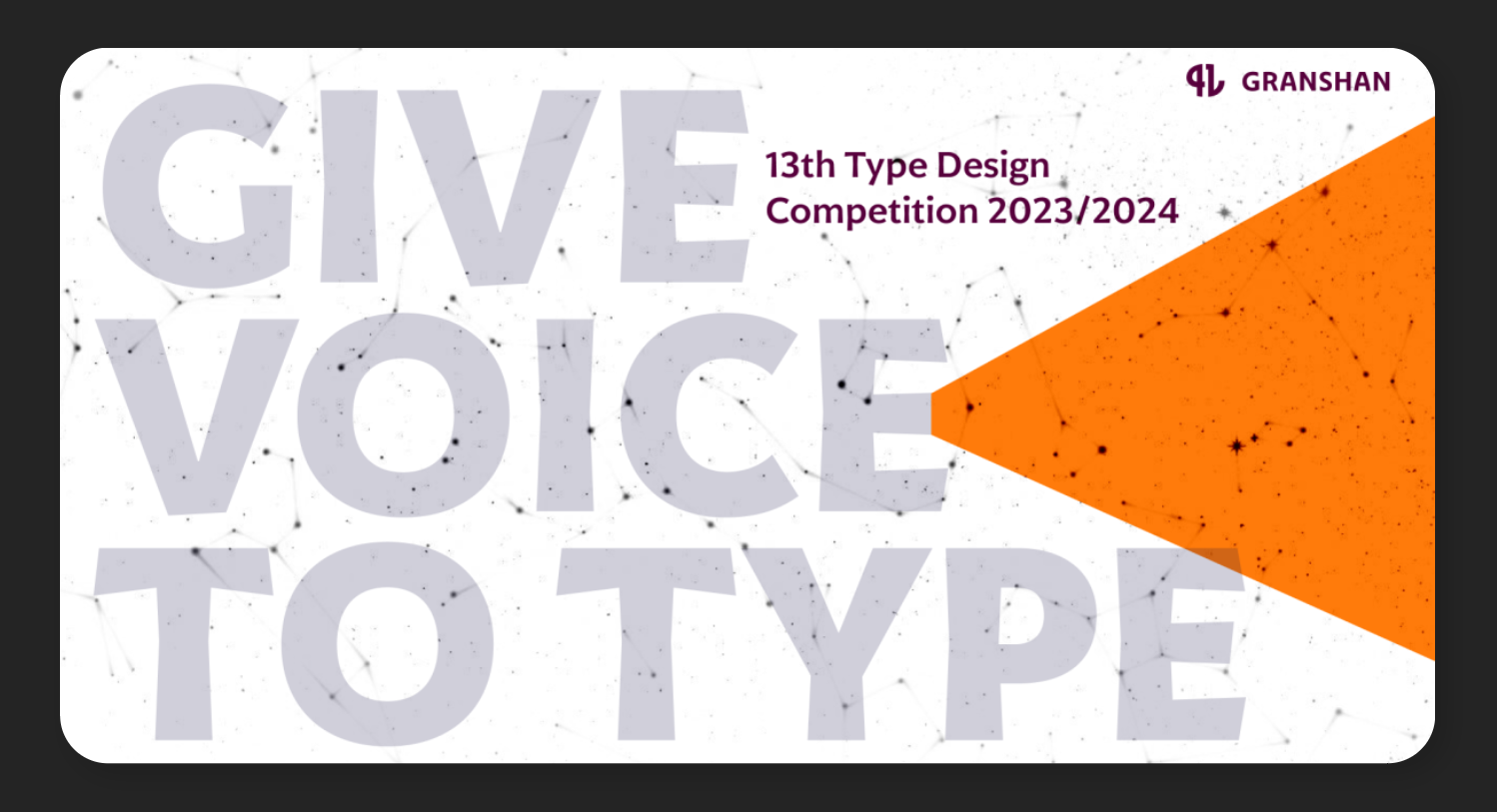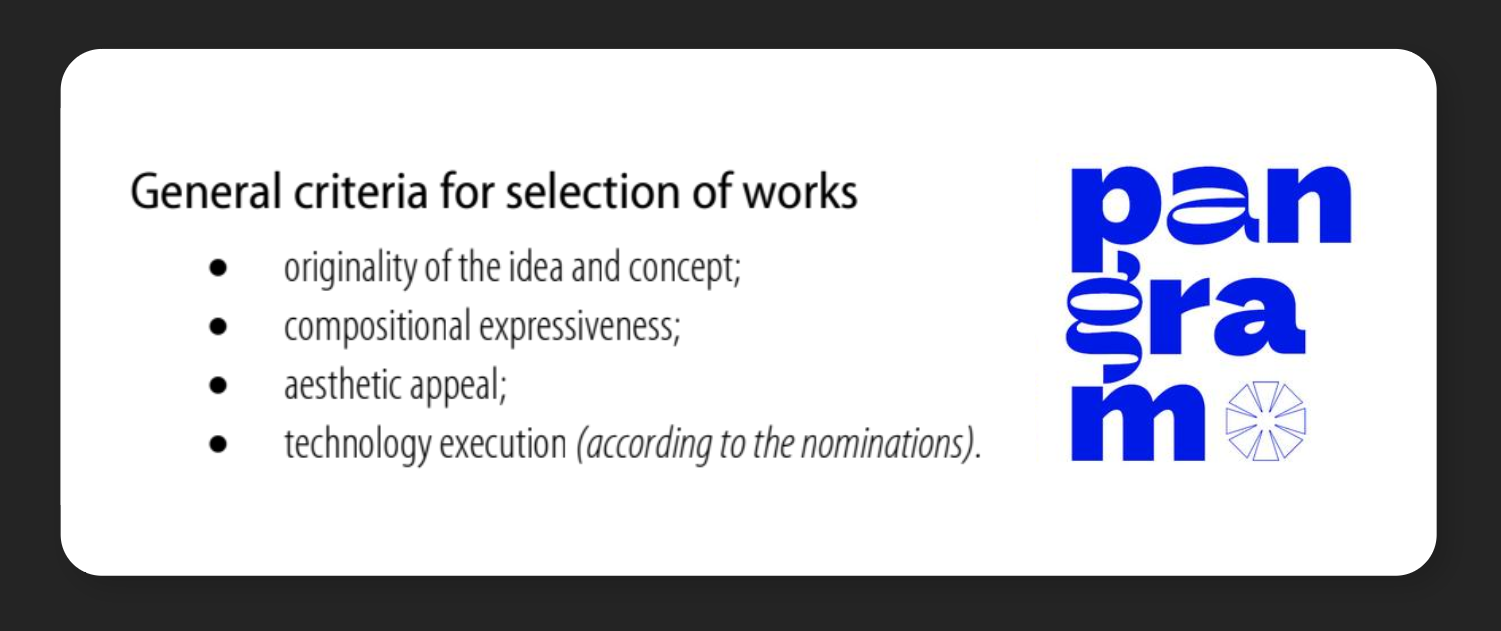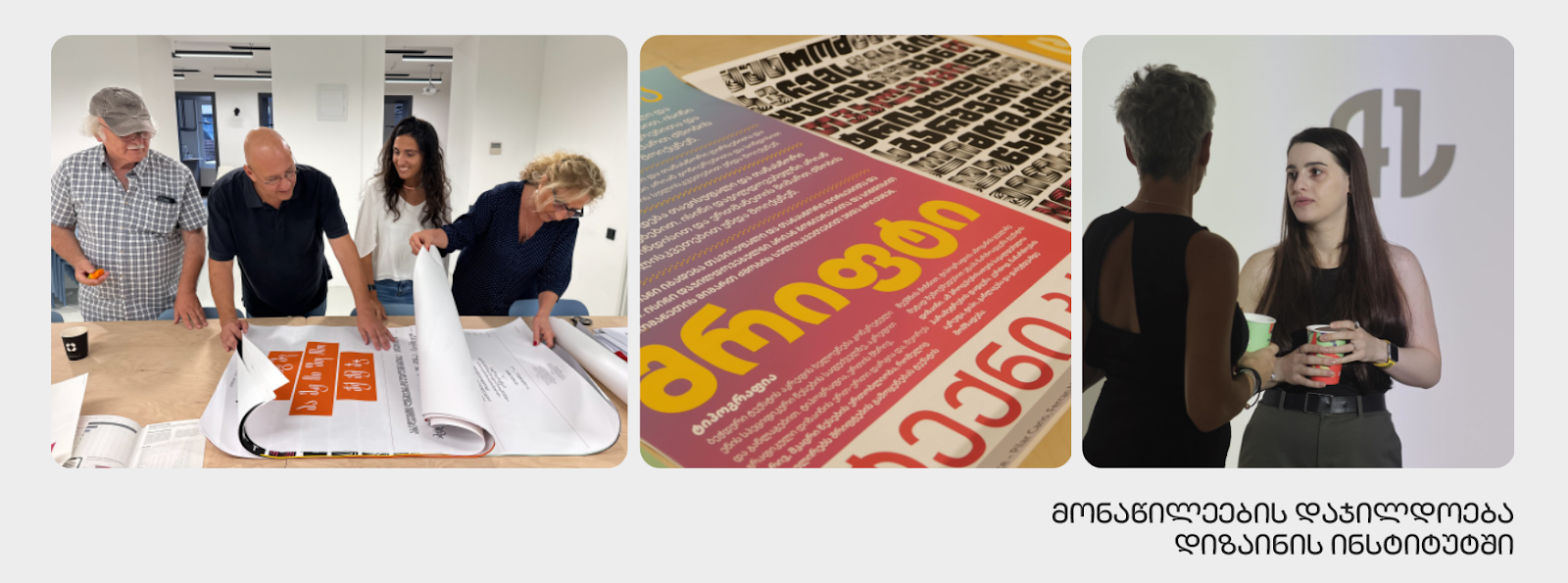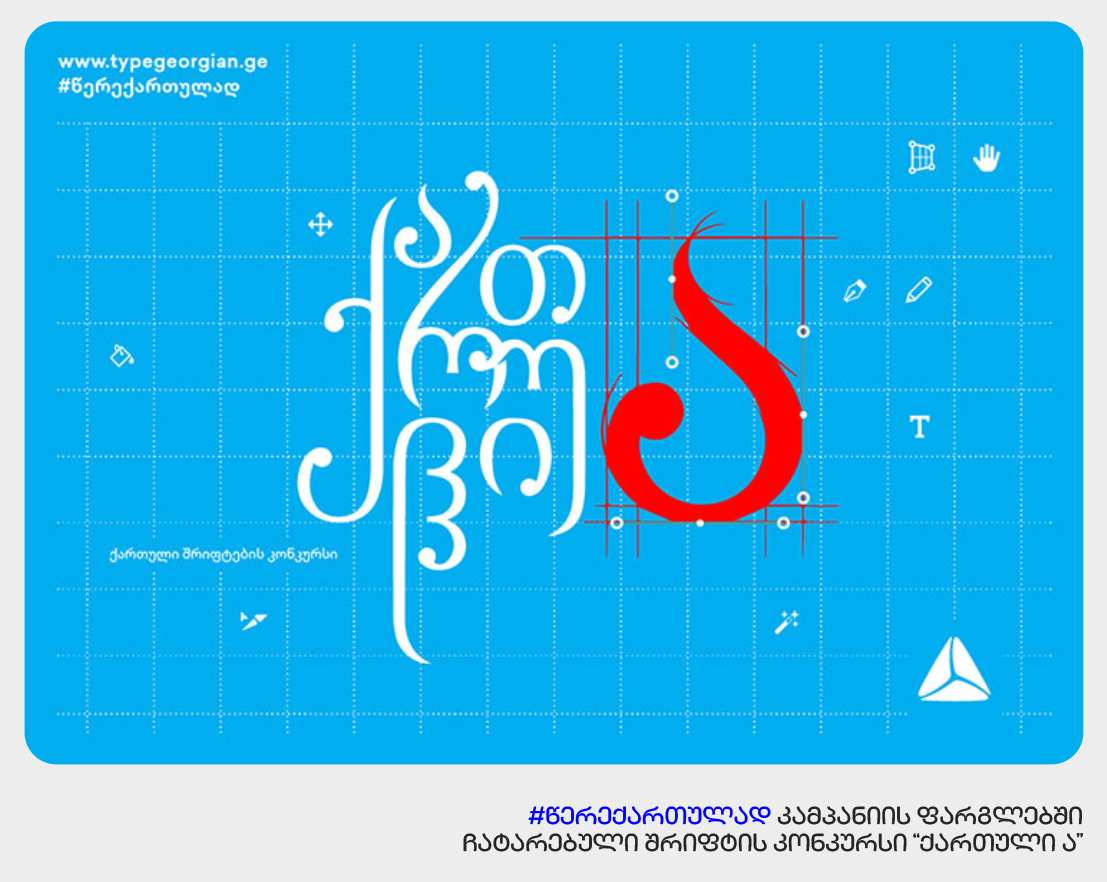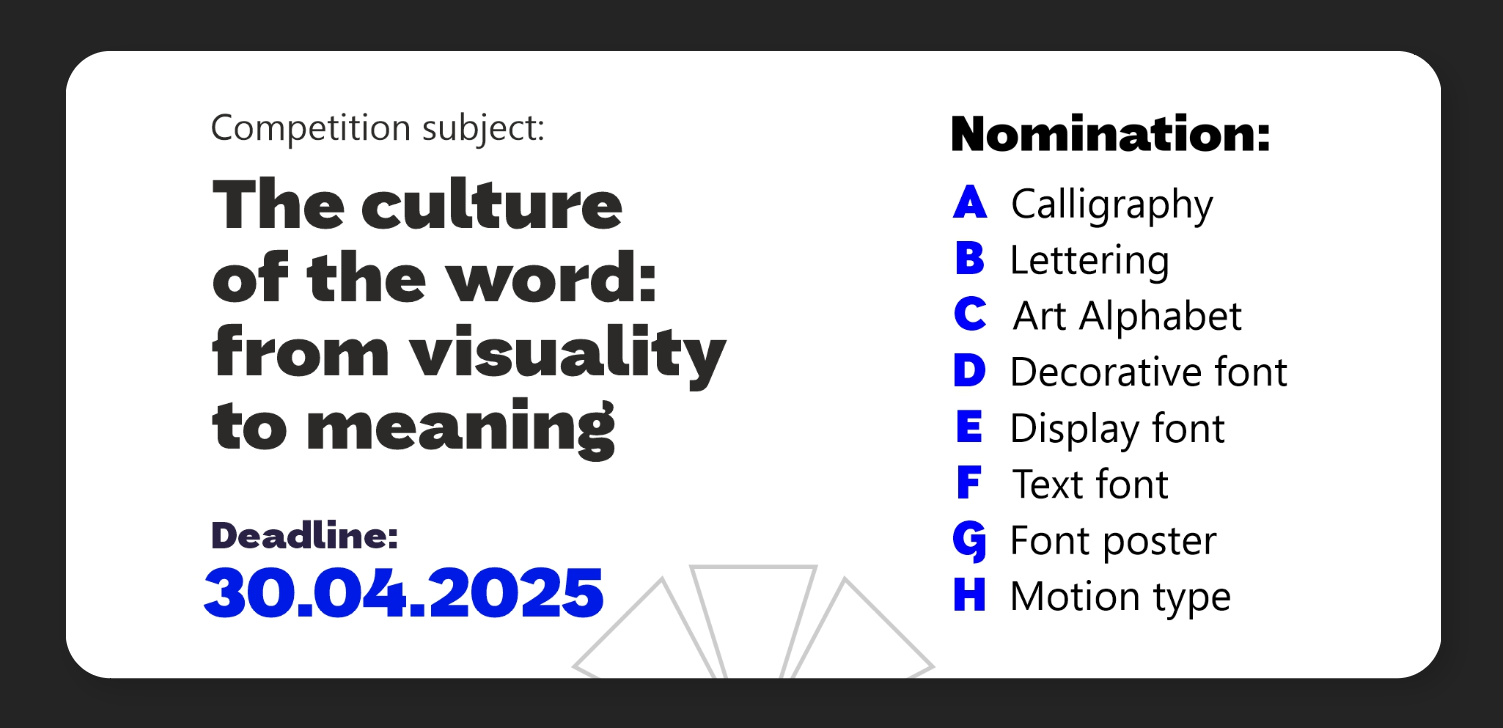
ფონტის დიზაინერი მერაბი გეწაძე უკვე მესამე წელია, რაც უკრაინული საერთაშორისო კონკურსის Pangram - International Student Competition on Font and Calligraphy-ის ჟიურის წევრია. ეს ფაქტი კიდევ ერთხელ უსვამს ხაზს მის პროფესიონალიზმს და იმ ნდობას, რომელსაც საერთაშორისო ტიპოგრაფიული სივრცე ავლენს ქართული დიზაინის მიმართ.
ბოლო წლებში ქართული ფონტების ხილვადობა გლობალურ არენაზე მნიშვნელოვნად გაიზარდა. ამის მაგალითია Granshan-ის მე-13 საერთაშორისო არალათინური შრიფტის კონკურსი, სადაც ქართული ანბანი ოფიციალურად დაემატა კონკურსში მონაწილე დამწერლობათა სიას, როგორც მეათე და მერაბი ასევე ჟიურის წევრებს შორის იმყოფებოდა. აღსანიშნავია, რომ სწორედ იმ წელს ქართველმა დიზაინერმა, ანა სანიკიძემ, პირველი ადგილი და კონკურსის მთავარი პრიზი მოიპოვა, ხოლო სხვა ქართველმა მონაწილეებმაც (ნიკა ხიპაშვილი, ლაშა გიორგაძე,ალექსანდრე სუკიასოვი, სერგო ტიტენკოვი) არაერთი პრიზი მიიღეს სხვადასხვა კატეგორიებში.
ალბათ ყველა დიზაინერისთვის საინტერესოა, როგორ მიიღოს მონაწილეობა კონკურსში, როგორ აფასებს საერთაშორისო კონკურსში მონაწილეებს ჟიური და რა გავლენას ახდენს კონკურსებში ქართველების ხილვადობა ქართული შრიფტის დიზაინის მომავალზე. ამაზე სასაუბროდ მერაბ გეწაძეს დავუკავშირდით:
გილოცავთ Pangram-ის შრიფტების კონკურსის ჟიურის წევრად კიდევ ერთხელ შერჩევას! როგორც ვიცით, უკვე მესამე წელია, რაც ჟიურის წევრებს შორის ხართ საქართველოს სახელით. როგორ ჩაერთეთ პირველად კონკურსში?
მადლობა, რომ დაინტერესდით ამ თემით, მსგავსი პუბლიკაციები ხელს უწყობს ქართული დამწერლობისა და შრიფტის მნიშვნელობის პოპულარიზაციას თანამედროვე საზოგადოებაში.
“PANGRAM”-ის კონკურსის ჟიურიში ჩართვა შემომთავაზა „გრანშანის“ ერთერთმა დამფუძნებელმა ედიკ ღაბუზიანმა. ჟიურიში ჩვენი წარმომადგენლის დამატება თავისთავად აჩენს კონკურსში ქართველი მონაწილეების აქტიურობის მოლოდინს.
რას ნიშნავს თქვენთვის საქართველოს წარმოჩენა ასეთ ცნობილ საერთაშორისო კონკურსში?
ქართველ მონაწილეთა ნებისმიერი საერთაშორისო აქტივობა მნიშვნელოვანია ზოგადად საქართველოს და ამ შემთხვევაში ქართული დამწერლობის პოპულარიზაციისათვის. თუ გავითვალისწინებთ ჟიურის და იმას, რომ მონაწილეთა მრავალეროვნული შემადგენლობის თვალთახედვაში ქართული დამწერლობის ნიმუშები მოხვდა, „Pangram“-ი სასარგებლო და მნიშვნელოვანი სივრცეა, როგორც ქართული დამწერლობის გაცნობისათვის, ასევე სტუდენტთა სტიმულირებისა და სამომავლოდ პროფესიონალებად ჩამოსაყალიბებისთვის.
თქვენი აზრით, რით არის Pangram-ის შრიფტების კონკურსი უნიკალური - რით განსხვავდება ის სხვა შრიფტების დიზაინის კონკურსებისგან?
ყველა კონკურსი თავისთავად უნიკალურია. „Pangram“-ის ყოველ ახალ კონკურსს გააჩნია თავისი თემა-დევიზი, რაზეც მორგებულია მთლიანად საკონკურსო ნამუშევრების ხასიათი.
გარდა ამისა, წარმოდგენილი ნიმუშები თავისი ვიზუალური თუ შემოქმედებითი ჩანაფიქრით ფართო დიაპაზონისაა და ზოგჯერ ცდება კიდეც შრიფტის სახასიათო ტრადიციულ ზღვარს, რაც არაა მოულოდნელობა ავტორთა ახალგაზრდული თამამი აზროვნების გათვალისწინებით.
რამდენად დაინტერესებულები არიან და აქტიურად ერთვებიან თუ არა ქართველი დიზაინერები Pangram-ის კონკურსში?
ქართველი ავტორების აქტიურობა კონკურსში სასურველზე მცირეა. მიუხედავად იმისა, რომ რამდენადაც შეგვიძლია მოვუწოდებთ მონაწილეობისაკენ, ვფიქრობ, საჭიროა დრო, რომ პოპულარული გახდეს კონკურსი.
როგორც ჟიურის წევრი, რა არის ყველაზე მნიშვნელოვანი თვისებები, რომლებსაც ეძებთ შრიფტში?
ერთი გამორჩეული თვისება, რაც განაპირობებს შრიფტის შეფასების ხარისხს - არ მაქვს. კონკურსი რამდენიმე კატეგორიას მოიცავს და შესაბამისად შეფასების მიდგომებიც სხვადასხვაა. ძირითადი კრიტერიუმებია: ორიგინალობა, კომპოზიციური მიმზიდველობა, ესთეტიური გამომსახველობა და შესრულების ტექნური მხარე.
როგორ აბალანსებთ ტექნიკური სიზუსტის შეფარდებას კრეატიულობასთან და ორიგინალურობასთან ნამუშევრების შეფასებისას?
რადგან ჟიურის წევრებს მხოლოდ რასტრული გამოსახულებები გვეგზავნება და არა ვექტორული, ტექნიკური სიზუსტის შეფასება ხილულ ზღვარს არ ცდება. სამაგიეროდ, ასეთი გამოსახულება საკმარისია ნამუშევრის სხვა კრიტერიუმებით შესაფასებლად. ჩემი შეხედულებით, წარმოდგენილ ნიმუშებში ტექნიკური სრულყოფა ავტორთა მიერ არცაა პირველხარისხოვანი და პრიორიტეტი უფრო ორიგინალობაზე და შემოქმედებით მიგნებებზე კეთდება.
მოდით, ვისაუბროთ GRANSHAN-ის კონკურსზე. თქვენ იქაც საქართველოს წარმომადგენელი ჟიურის წევრებს შორის იყავით, რაც დიდი მიღწევაა. რით განსხვავდებოდა ეს გამოცდილება Pangram-ისგან?
GRANSHAN-ი თავიდანვე პროფესიონალების ჩართულობაზეა ორიენტირებული და შესაბამისად დონეც უფრო მაღალია. ნამუშევრების ვიზუალზე მოთხოვნა ბევრად უფრო დეტალურია და რამდენიმე შაბლონშია წარმოდგენილი, რაც განაპირობებს მაქსიმალურად კრიტიკულად იქნეს შეფასებული ხარისხი. თავდაპირველად, დამწერლობის ჟიურის ყველა წევრის მიერ ხდება ნამუშევრების განხილვა და შეფასება. შემდეგ ეტაპზე შეფასებაში მონაწილეობენ მხოლოდ ათივე დამწერლობის ჟიურის თავმჯდომარეები და კონკურსის ორგანიზატორებთან ერთად ხდება საბოლოო გამარჯვებულების გამოვლენა.
გარდა კონკურსისა GRANSHAN-ი ატარებს კონფერენციებს მსოფლიოს სხვადასხვა ქალაქებში, სადაც მომხსენებლებად არიან შრიფტის დიზაინის სფეროს როგორც აღიარებული, ასევე ნებისმიერი სპეციალისტები.
GRANSHAN-ის მე-13 შრიფტის კონკურსში (2023/2024) ქართული ოფიციალურად შეიყვანეს წარმოდგენილ დამწერლობებს შორის. რამდენად მნიშვნელოვანი იყო ეს ნაბიჯი ჩვენი ტიპოგრაფიული კულტურისთვის?
კონკურსში ქართული დამწერლობის მეათე ნომინაციად შეყვანა ერთბაშად არ მოხდარა. მას წინ უძღოდა რამდენიმეწლიანი მიმოწერა და ონლაინ ჩართვები ასოციაცია „ქართული შრიფტისა“ და GRANSHAN-ის ორგანიზატორებს შორის. ამ პროცესის ინიციატორი, საქართველოს მხარის წარმომადგენელი და ჟიურის თავმჯდომარე იყო ნინო ჯიშკარიანი. ჟიურის კი დავემატეთ სამი წევრი საქართველოდან. მე პირადად მქონდა ქართველ მონაწილეთა მცირე აქტივობის მოლოდინი, რაც საბედნიეროდ არ გამართლდა და საკმარისი რაოდენობის კონკურსანტმა მიიღო მონაწილეობა. არსებული კონკურენცია კარგი სტიმულია პროფესიონალურ ზრდისა და შრიფტის ხარისხის ამაღლებისთვის.
ამასთან, სასურველია მედიაში უფრო თამამად გამოიყენონ ასო-ნიშნების გრაფიკა და მისი დიზაინი.